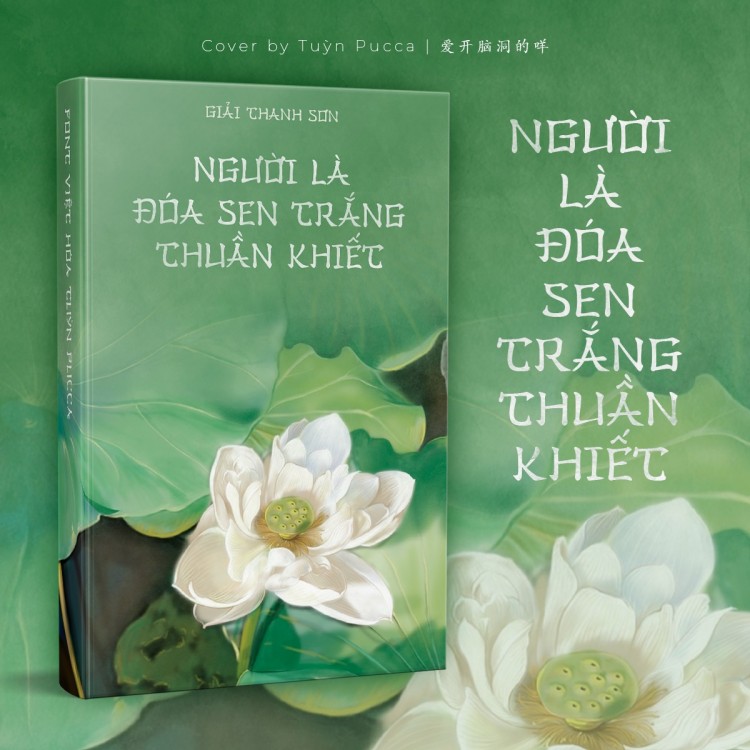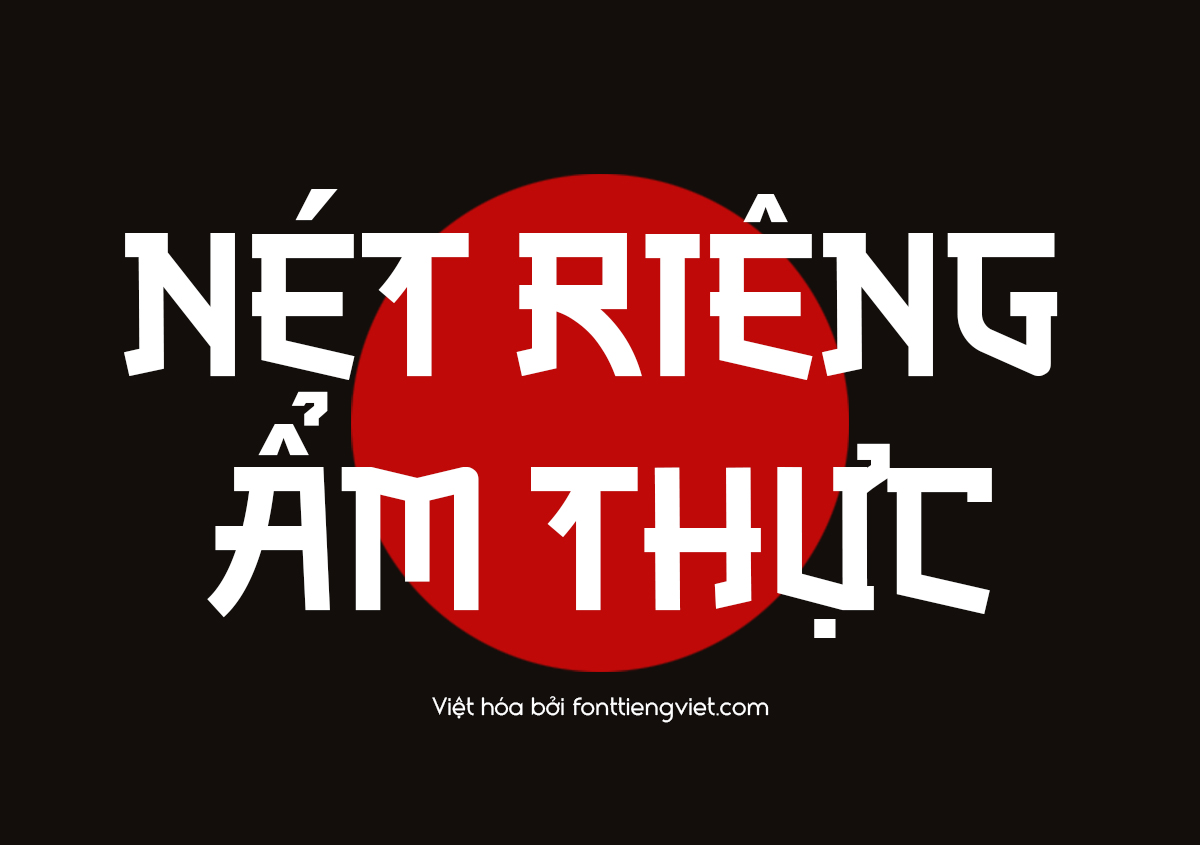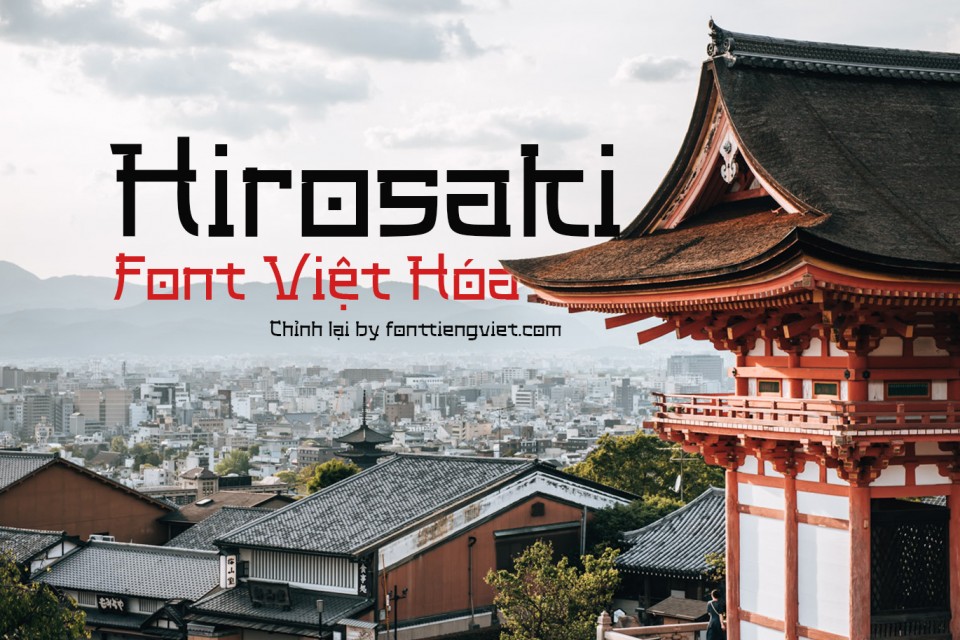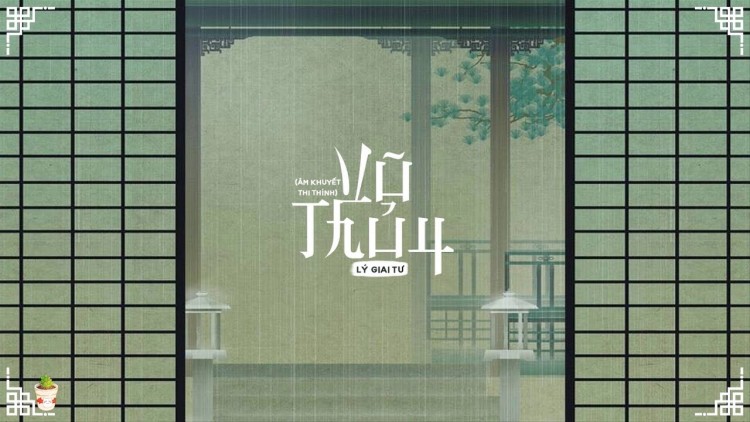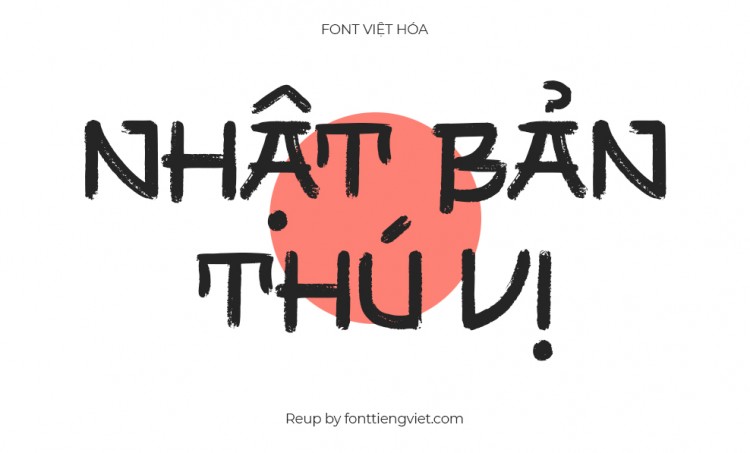
Tổng hợp 10 Font Nhật Bản (Japan Font) đẹp
Bạn đang băn khoăn không biết chọn font tiếng Nhật nào phù hợp cho công việc hay việc học tập? Việc lựa chọn đúng font có thể giúp bạn nâng cao trải nghiệm đọc và thể hiện nội dung một cách rõ ràng, thẩm mỹ hơn. Đừng lo, hãy cùng FPTMEDIA Shop khám phá ngay hơn 10 font tiếng Nhật đẹp và phổ biến, được tuyển chọn kỹ lưỡng để đáp ứng nhiều nhu cầu sử dụng khác nhau
Font tiếng Nhật là gì?
Tiếng Nhật ngày nay đã trở nên quen thuộc với nhiều người trên thế giới nhờ hệ thống chữ viết độc đáo và giàu bản sắc. Khác với bảng chữ cái Latinh, tiếng Nhật sử dụng ba hệ thống chữ cái chính: Hiragana, Katakana và Kanji (Hán tự), mỗi loại đều mang những đặc điểm riêng và phản ánh rõ nét văn hóa đặc trưng của đất nước mặt trời mọc.
Để việc đọc, viết và tiếp cận tiếng Nhật trở nên hiệu quả hơn, việc lựa chọn font chữ phù hợp là điều rất quan trọng. Các font tiếng Nhật không chỉ phục vụ cho nhu cầu học tập và nghiên cứu, mà còn là công cụ đắc lực trong thiết kế sáng tạo, giúp truyền tải nội dung một cách thẩm mỹ và chuyên nghiệp.
Tổng hợp các font tiếng Nhật đẹp, phổ biến
Font việt hóa Hirosaki
Font Việt hóa Hirosaki là một kiểu chữ mang phong cách Nhật Bản với thiết kế đặc trưng, thường được sử dụng trong các dự án liên quan đến văn hóa Á Đông, đặc biệt là Nhật Bản. Khi được Việt hóa, font vẫn giữ được tinh thần truyền thống của bản gốc nhưng hỗ trợ đầy đủ các ký tự tiếng Việt, bao gồm dấu và chữ cái đặc biệt, giúp người dùng dễ dàng sử dụng trong thiết kế và trình bày nội dung tiếng Việt.
Font việt hóa Akisa
Font Việt hóa Akisa là một kiểu chữ mang đậm phong cách Nhật Bản hiện đại, được thiết kế với các nét chữ mềm mại, thanh thoát nhưng vẫn giữ được sự mạnh mẽ, cá tính. Sau khi được Việt hóa, font Akisa hỗ trợ đầy đủ ký tự tiếng Việt, giúp người dùng sử dụng dễ dàng cho cả nội dung tiếng Việt lẫn tiếng Nhật hoặc các thiết kế liên quan đến văn hóa Á Đông.
Font việt hoá Han Zi
Font Việt hóa Han Zi là một kiểu chữ mang đậm phong cách Á Đông, lấy cảm hứng từ thư pháp Trung Hoa hoặc các bộ chữ Hán cổ điển. Khi được Việt hóa, font Han Zi không chỉ giữ nguyên vẻ đẹp cổ kính, nghệ thuật mà còn hỗ trợ đầy đủ ký tự tiếng Việt, giúp dễ dàng ứng dụng trong thiết kế và sáng tạo nội dung.
Font việt hóa Shikamaru
Font Việt hóa Shikamaru là một kiểu chữ độc đáo lấy cảm hứng từ phong cách Nhật Bản hiện đại, thường gợi liên tưởng đến anime, manga hoặc các thiết kế mang đậm tinh thần trẻ trung, năng động. Khi được Việt hóa, font Shikamaru vẫn giữ nguyên cá tính mạnh mẽ của bản gốc nhưng đồng thời hỗ trợ đầy đủ các ký tự tiếng Việt, rất tiện lợi cho người dùng Việt Nam trong các dự án sáng tạo.
Font việt hoá Romaji Mincho
Font Việt hóa Romaji Mincho là một kiểu chữ serif mang phong cách truyền thống Nhật Bản, đặc trưng bởi các đường nét thanh mảnh xen lẫn các nét dày dặn — thể hiện rõ tinh thần của dòng Mincho (明朝体) trong hệ thống chữ Nhật. Sau khi được Việt hóa, font Romaji Mincho không chỉ giữ nguyên vẻ đẹp cổ điển Á Đông mà còn hỗ trợ đầy đủ tiếng Việt, phù hợp cho nhiều mục đích sử dụng sáng tạo và chuyên nghiệp.
Font việt hoá Bladerunner
Font Việt hóa Bladerunner là kiểu chữ lấy cảm hứng từ bộ phim khoa học viễn tưởng kinh điển Blade Runner. Font này mang đậm phong cách cyberpunk với các nét chữ sắc cạnh, tương lai và hơi hướng công nghệ cao. Khi được Việt hóa, font Bladerunner vẫn giữ nguyên “chất viễn tưởng” của bản gốc và đồng thời hỗ trợ đầy đủ các ký tự tiếng Việt – rất phù hợp cho các dự án sáng tạo mang màu sắc sci-fi hoặc công nghệ.
Font chữ tiếng Nhật không chỉ là công cụ hỗ trợ đọc viết, mà còn phản ánh chiều sâu văn hóa và thẩm mỹ đặc trưng của xứ sở hoa anh đào. Từ những nét mềm mại của Hiragana đến đường nét sắc sảo của Kanji, mỗi font chữ đều mang trong mình một cá tính riêng, phù hợp với từng mục đích sử dụng như học tập, thiết kế sáng tạo hay truyền thông thị giác. Việc lựa chọn đúng font chữ tiếng Nhật không chỉ giúp tăng tính thẩm mỹ mà còn góp phần truyền tải thông điệp một cách hiệu quả và tinh tế hơn. Mong rằng danh sách font Nhật được giới thiệu sẽ là nguồn cảm hứng hữu ích cho bạn trong hành trình học tập và sáng tạo.